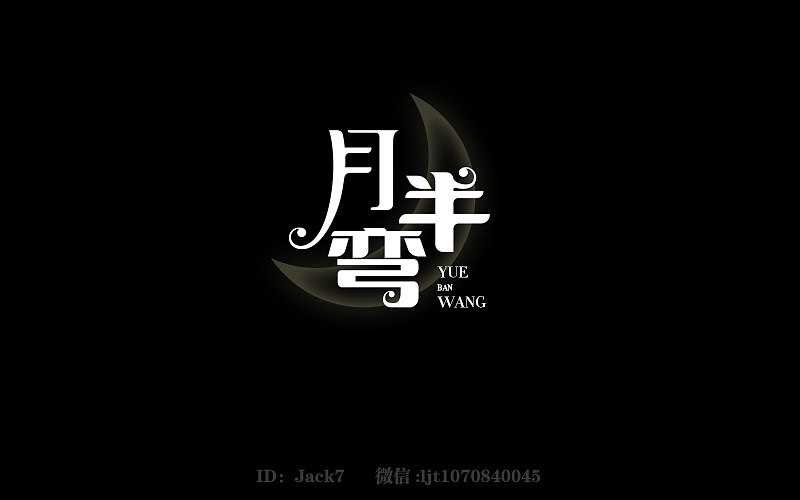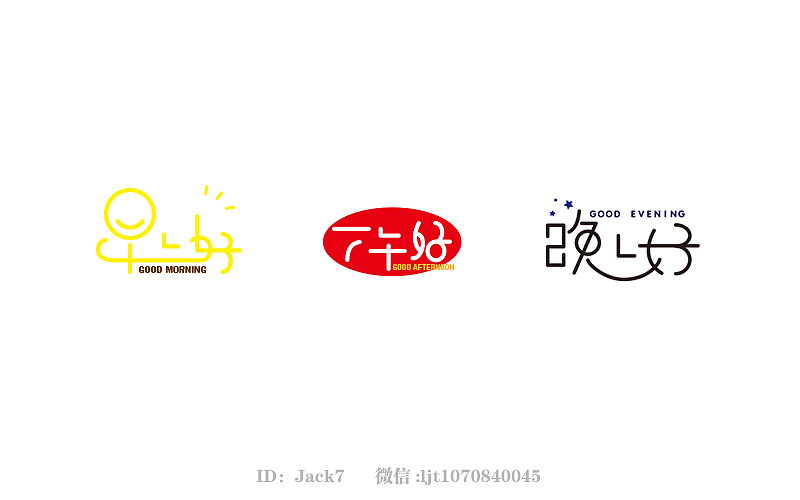
最近几个星期在学字体设计,今天发布也是最近的练习,之前一直没觉得字体是需要设计的,做的时候都是直接用字库上得字体或者稍微改下就用了。虽然也知道字体设计这回事不过没怎么放在心上,后来2015年过年期间我突然觉得字体设计是挺有意思的,挺好玩,字体也是真的需要去设计的,现在也觉得当时的想法是错误的。个人觉得,字体设计有时可以很简单就可以加上创意让其与众不同,有时需要花很长时间去琢磨,不过字体设计可以因为某个创意点而让我们眼前一亮,也让字活起来了一样,这也是字体设计的魅力所在吧!
想念我老弟了突然,想起我们小时候的球衣后面就是打着这4个字,所以就做了
嘟嘟的笨小孩
最近一直和基友在打这个游戏
这个也可以看是看英文记单词了我觉得嘿嘿
比较杂的字体,平时练习
曾经有份感情放在我面前,让我到现在都想放下
月半弯是我听到陈坤的这首歌的时候心血来潮时做的,哈哈
高中时代是比较青涩的吧